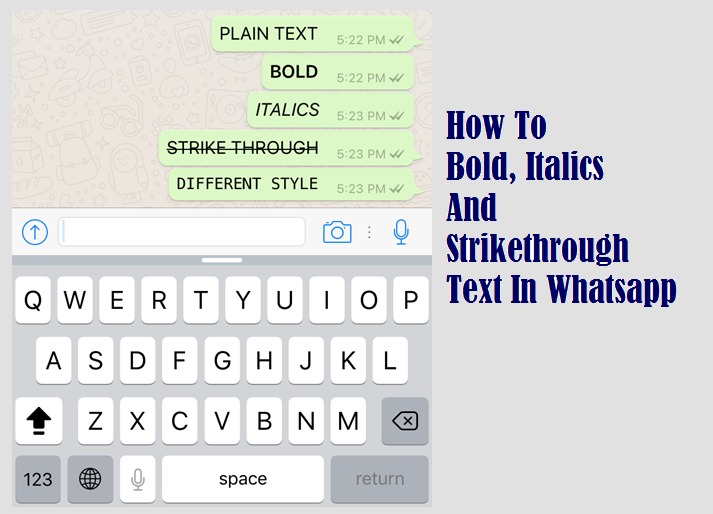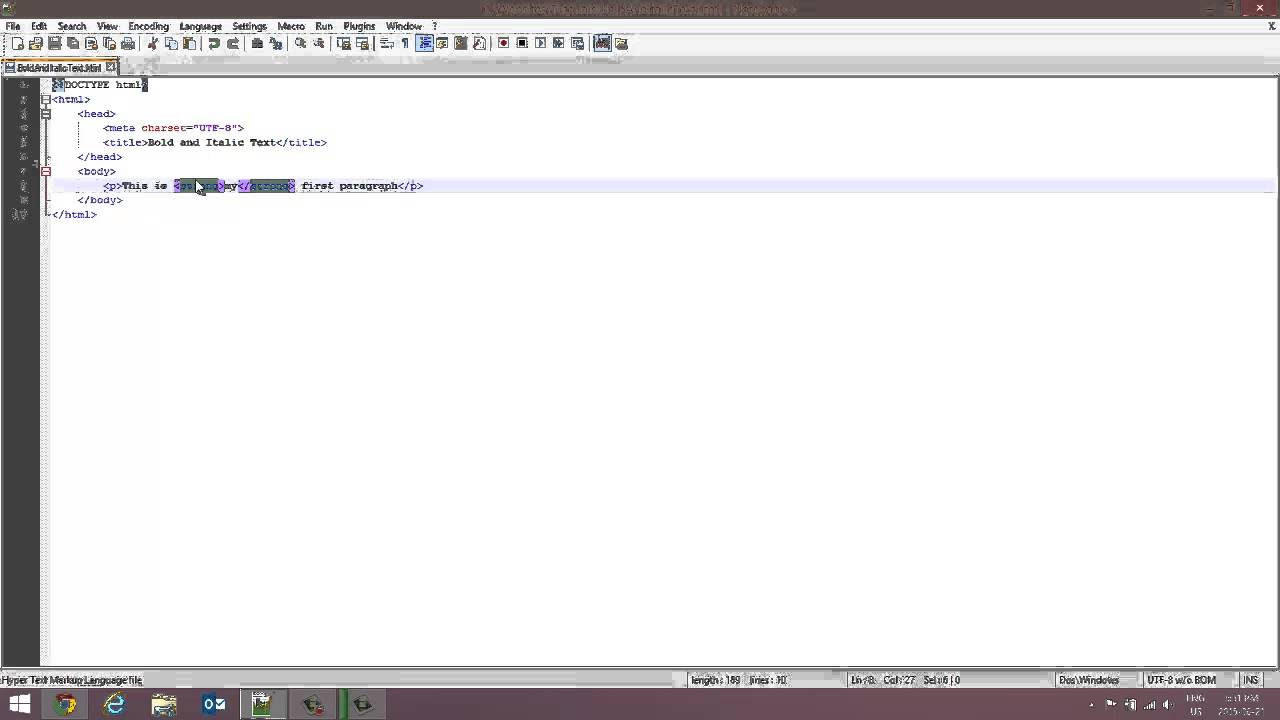
типографика. Следует ли также выделить жирным шрифтом пробелы вокруг жирного текста?
На следующем изображении верхний текст содержит обычные пробелы вокруг жирного слова bar , а нижний текст содержит пробелы, выделенные полужирным шрифтом:
Я добавил красные вертикальные маркерные линии, чтобы было легче увидеть, что слова не совпадают идеально. Для некоторых шрифтов это не имеет значения, однако для других (например, Avenir) имеет значение.
Есть ли общее правило, которому я должен отдать предпочтение? Если я сделаю слово жирным шрифтом , должен ли я также выделить оба пробела вокруг него жирным шрифтом?
(и если это не слишком расширяет вопрос, как насчет курсив
Нет, пробелы не должны быть жирными, потому что это было бы плохой семантикой.
Слово или последовательность слов можно выделить жирным шрифтом, но пробелы вокруг слова нельзя.
Это отдельно от любых мыслей о визуальном дизайне и независимо от какой-либо реализации. Семантика исходит от писателя. Им не до дизайнера. У дизайнера есть инструменты визуального дизайна для визуального оформления. Опять же, в любой реализации.
В вашем примере писатель написал:
foo **bar** baz
У автора нет причин выделять пробелы жирным шрифтом, потому что нет семантической причины выделять пробелы жирным шрифтом. Жирный текст исходит от мысли писателей. Они выделяют слово (или ряд слов) жирным шрифтом, а не пробелы.
Итак, HTML — пример в HTML, потому что ваш пример в HTML, но это применимо к любой реализации — из приведенного выше Markdown:
foo bar baz
… и это после , когда начинается визуальный дизайн.
Если вам по какой-то причине нужно дополнительное пространство вокруг выделенного жирным шрифтом текста — и вы работаете в HTML, как следует из вашего примера — вы используете CSS или JavaScript для изменения DOM, вы не разрушаете семантику HTML. Если вы работаете в InDesign, Illustrator или любой другой среде визуального дизайна, то же самое.
Если вы посмотрите на пример с реальным письмом, то станет яснее:
Опасно Не ешьте содержимое пакета.
… это слово «Опасность» выделено жирным шрифтом. Ничего больше.
Честно говоря, я не думаю, что это имеет значение. Любая разница в интервалах будет незначительной и незаметной. Тем не менее, это то, что я обычно делаю.
Любая разница в интервалах будет зависеть от шрифта. Если есть разница, дизайнер шрифта принял сознательное решение сделать это различие, так что используйте его.
Жирный шрифт по определению шире, чем его аналог обычного веса, поэтому любой интервал, который, вероятно, был тщательно рассчитан, чтобы соответствовать шрифту, естественно, должен быть одинаково шире. Дополнительное пространство (теоретически) повысит разборчивость и сбалансированность текста.
Помните, что нужно быть последовательным. Если вы используете жирный пробел с одной стороны, используйте его и с другой. В противном случае текст может выглядеть несбалансированным. Во многих программах, если вы дважды щелкните, чтобы выбрать слово, оно выделит слово и завершающий пробел, поэтому, если вы дважды щелкните и измените шрифт на полужирный, вы получите обычный пробел перед и полужирный пробел после.
Другие отмечают, что это семантически неверно. Это верно, если вы работаете с исходным кодом или разметкой, которые должны быть такими же правильными, как и визуальный вывод, но это не относится к делу.
Подводя итог — маловероятно, что кто-либо когда-либо заметит, но если вам не все равно — используйте шрифт так, как задумал его дизайнер, используйте жирные пробелы и используйте их последовательно.
На самом деле это имеет значение, и это хороший вопрос. У меня был опыт работы с некоторыми устройствами, когда пустое пространство не создавалось принудительно как сущность с содержимое отображалось бы неправильно, если бы пространство существовало в чем-то вроде тега span.
Например, foo bar отображается как foobar при кодировании как:
foo bar
Некоторые приложения, например InDesign, в HTML и CSS экспортируют его как:
Это пятница
В целом, это может быть на усмотрение разработчика, но это должно быть принято в рабочем процессе для обеспечения четности. Я бы посоветовал вам проверить, как это будет обработано на готовом продукте, поскольку это может сыграть важную роль в вашем развитии. Итак, чтобы ответить на ваш вопрос, когда я разрабатываю с использованием HTML, я не включаю конечные или начальные пробелы в свои теги span, поскольку у меня был опыт их игнорирования механизмом рендеринга с нескольких устройств.
foo bar
С точки зрения разработки следует учитывать поведение синтаксического анализа и удобство использования. Например, если вы разрабатываете словарь и планируете анализировать определенные элементы, которые могут быть включены в конкретный раздел, если вы включаете начальный и конечный интервалы в чем-то вроде тегов span или в элементе, это может иметь серьезные последствия для окончания.